现如今不管是做设计还是做广告,对字体的运用非常的多,不同的字体也有不同的风格与艺术表现力,所以在选择的时候肯定需要考虑到字体风格问题,如果字体是汉字或者是英文字,那么在选择字体的时候肯定有所影响,包括数字也是有一定影响的,那么数字用什么字体比较好呢?在选择字体的时候又该考虑哪些问题呢?
数字用什么字体比较好?肯定要考虑到哪个行业了,或者是运用于哪个领域了,如果是打印财务数据或者是办公软件数据使用,想要字体比较好看一点,那么可以选择宋体或者是黑体,这两种字体都是比较正规的,运用起来也会比较好看。
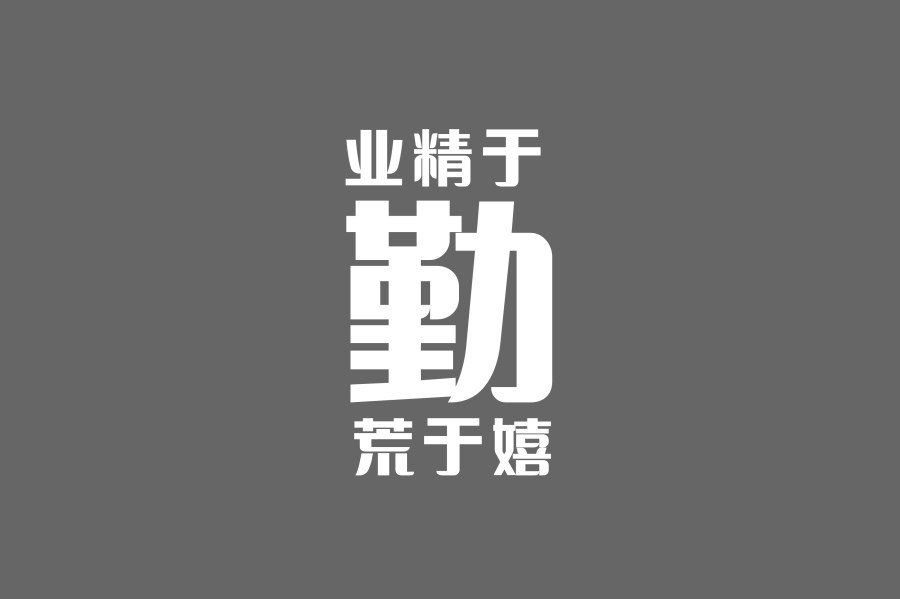
数字用什么字体比较好?不同的文件用的字体也会不一样,比较常规的文件或者是党政用的文件字体一般都选用黑体或者宋体,如果是艺术类个性文件,就可以选用创意字体或者艺术字体,字体符合文件需要的风格即可。
数字用什么字体比较好?如果是广告设计行业的话,那么这个字体的选择就比较广泛了,只需要看艺术表现力就可以了,任何一款字体都可能会被运用到。本身广告设计为的是吸引眼球,那么在选择字体的时候,肯定也会出于这个目的而选择不同的字体,在选择的时候完全可以考虑到艺术表现力。任何一款字体都是有自身魅力的,在选择的时候完全可以考虑到行业领域的需求,或者是想要表现的美感来做选择。